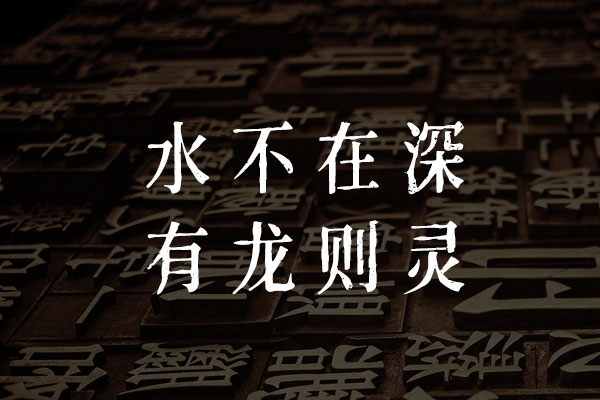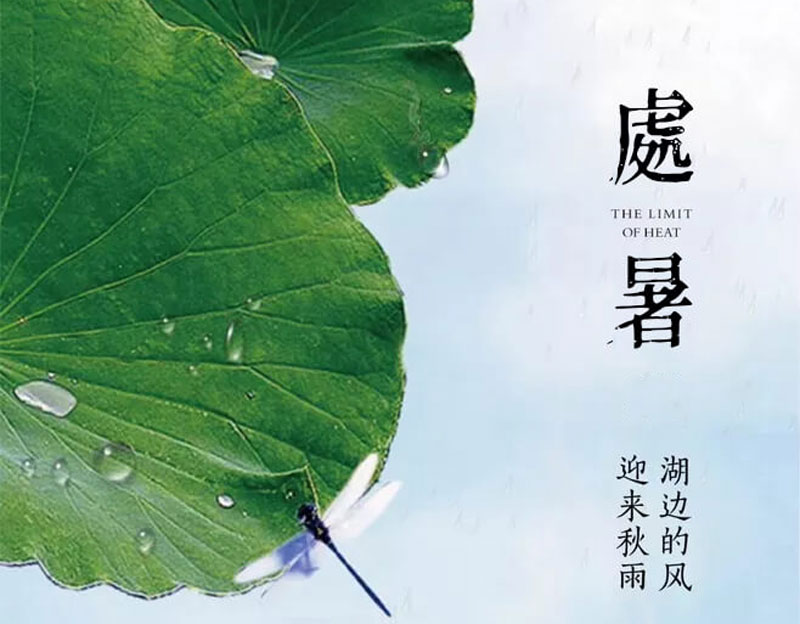
黄令东齐伋体
黄令东齐伋体,一款堪与康熙字典体媲美的免费商用字体,无需支付任何版权费用即可使用!此款字体源自明代木版印刷书籍《凌閔刻本》,通过半自动计算机视觉和OCR技术精心制作而成。其笔画风格蕴含着浓郁的书法特征,比常规的明朝体更具韵律感,散发着人文气息。
黄令东齐伋体(QIJIFALLBACK Regular)是基于思源宋体改造而来,因此具有很高的汉字覆盖率,无论是简体还是繁体都不会缺字。此外,这款字体遵循SIL Open Font License 1.1授权协议,可自由用于任何用途,包括免费商用。
黄令东齐伋体非常适合需要展现人文感、手作感、古拙感的场景。无论是在制作海报、标志设计,还是其他创意设计中,都能展现出独特的魅力和个性,为您的设计注入更多的灵性和活力!
黄令东齐伋体效果预览
黄令东齐伋体字体效果预览